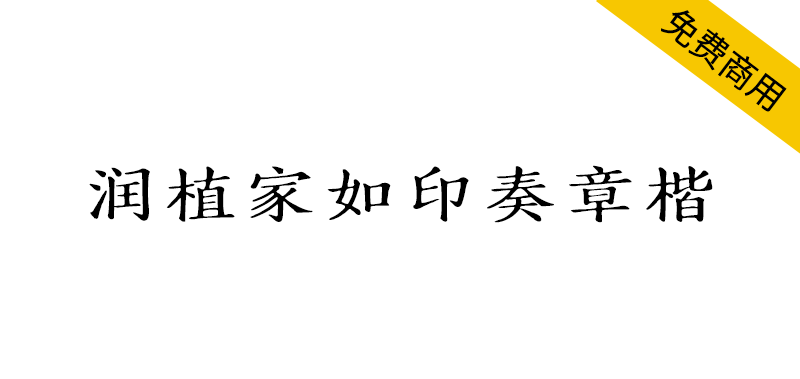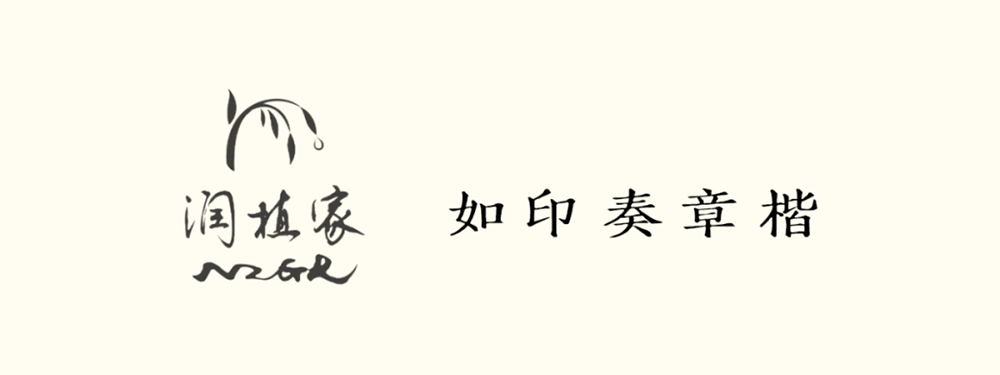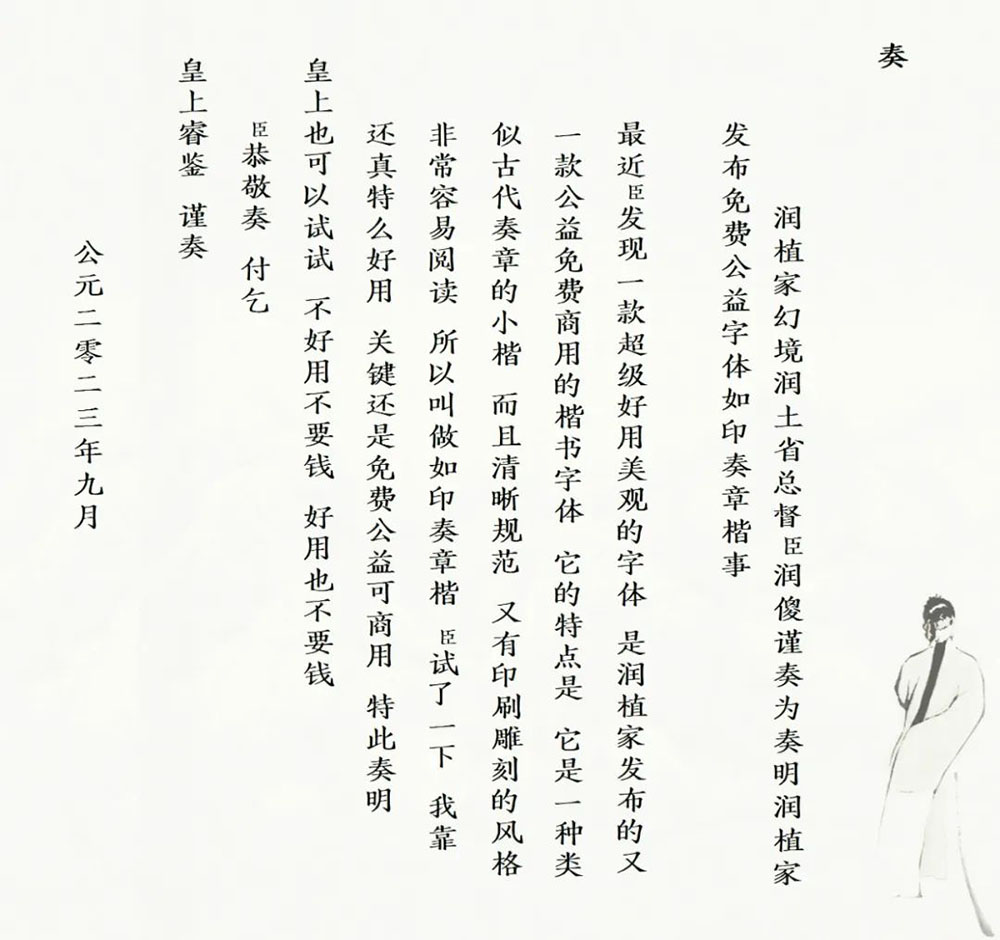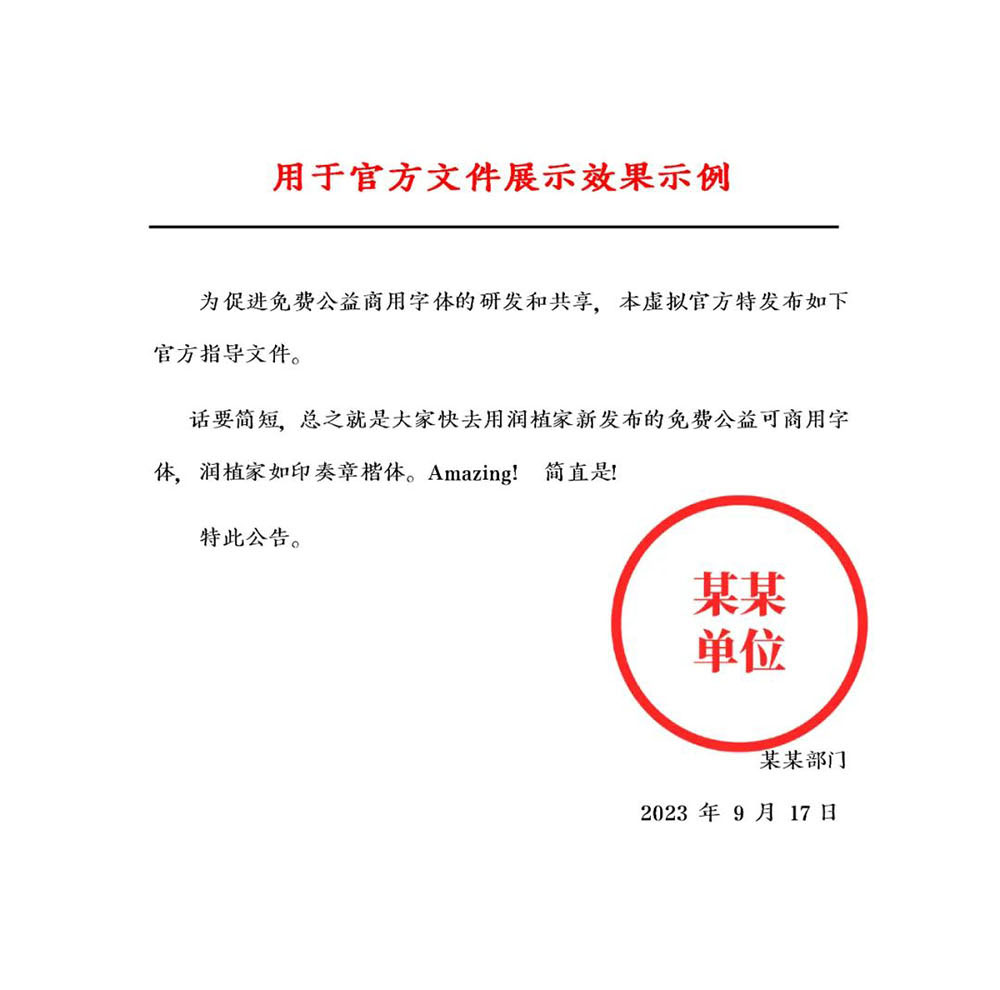
此前,润植家曾发布免费商用字体“润植家康熙字典美化体(常规款和清瘦款)”,免费商用简体宋体风格字体“润植家刻本简体”等,广受好评。但目前还有没适用于常规排版阅读、并且又古籍风格的简体楷体系列。今天,我们上线一款全新的楷体字体:润植家如印奏章楷!仍然是关注公众号,即可免费可商用的使用。
这款字体专用于大量文字,作为正文,竖排和横屏都好看,并且具有官方正式场合使用的气场,没有太大的违和感。
为什么叫如印奏章楷呢?因为这种规范中庸、有书卷气、可识别性高、适合长文阅读的字体,类似传统小楷书写的奏章,如果古代用这种字体写奏章,皇帝看了也会很舒服。但又非纯手写,有刊印风格,非常工整易读。
下面是模拟奏章的效果,是不是又平和工整、又养眼适合阅读?
同时,不光是直排的古代文字,横排也很好看,适合用于一些官方文件的展示哦,下面是用于官方文件展示的效果示例: